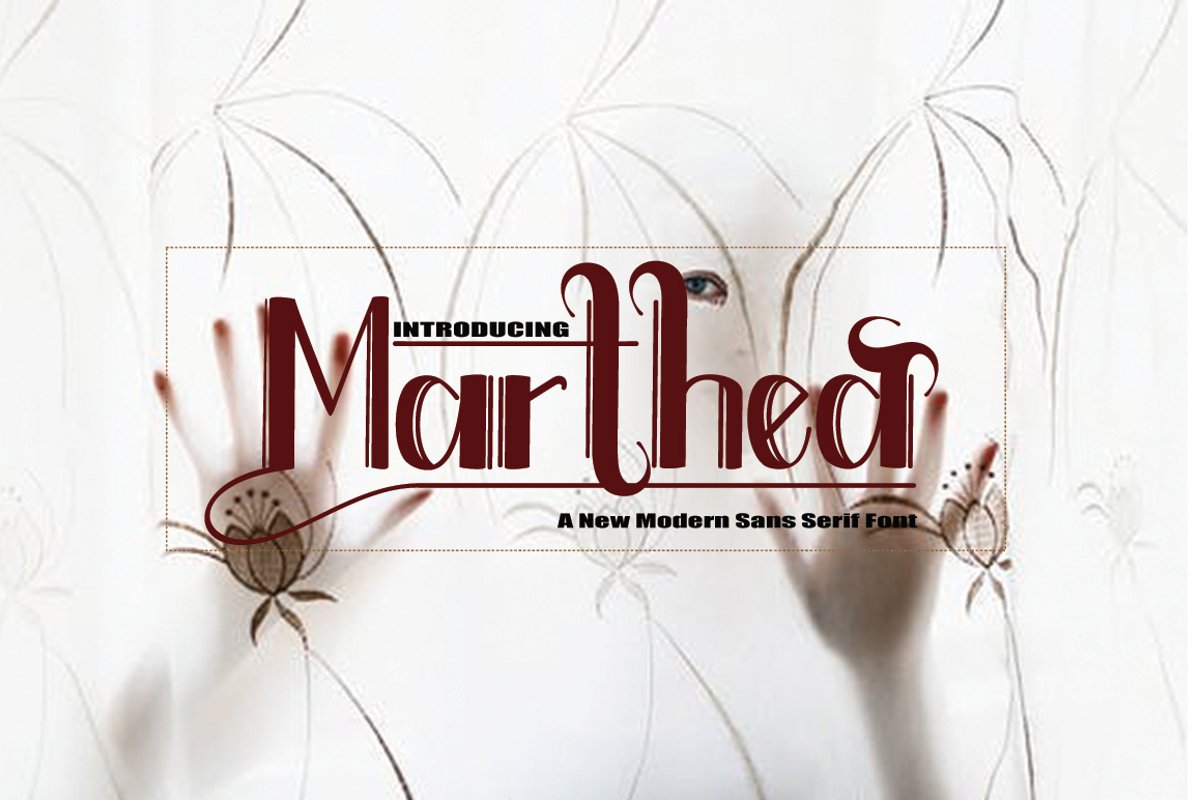
Marthea
Marthea adalah font Serif, tipografi dengan struktur yang tegas dan sangat nyaman bagi pembaca, juga memiliki karakter yang sederhana. sangat cocok untuk media resmi seperti spanduk, majalah, koran, buku, dan lainnya.